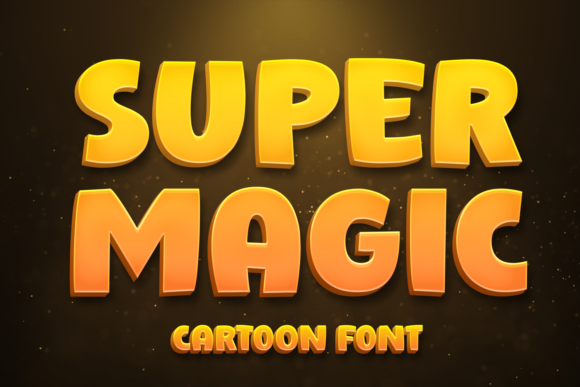
Super Magic Font
Super Magic Font – الخط الساحر الذي يمنح تصاميمك لمسة إبداعية فريدة! ✨
استمتع بخط احترافي يتميز بأسلوبه الأنيق والجذاب، مثالي للمصممين والمبدعين الذين يبحثون عن طابع مميز لمشاريعهم. سواء كنت تعمل على الشعارات، العناوين، التصاميم الإعلانية، أو حتى المنشورات على وسائل التواصل الاجتماعي، فإن Super Magic Font سيضفي لمسة سحرية على أعمالك.
✅ تصميم أنيق وحديث
امنح مشاريعك هوية بصرية لا تُنسى مع Super Magic Font! ????✨